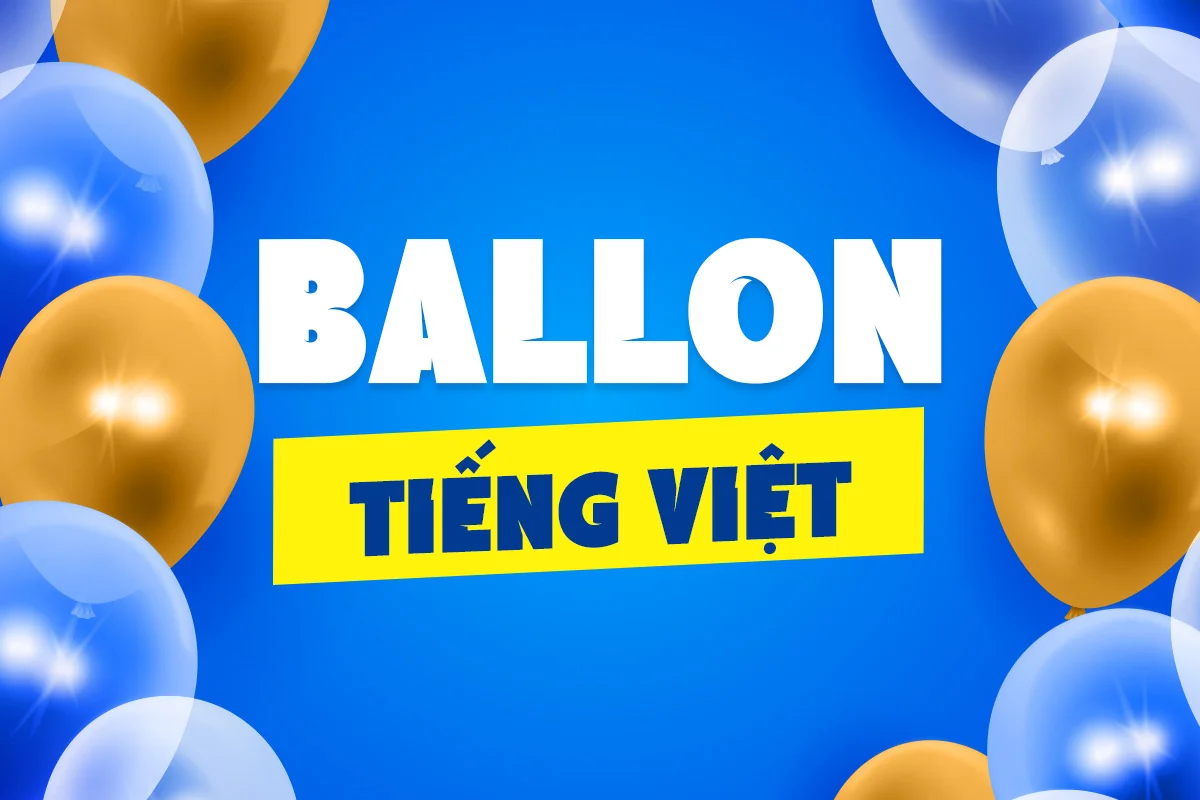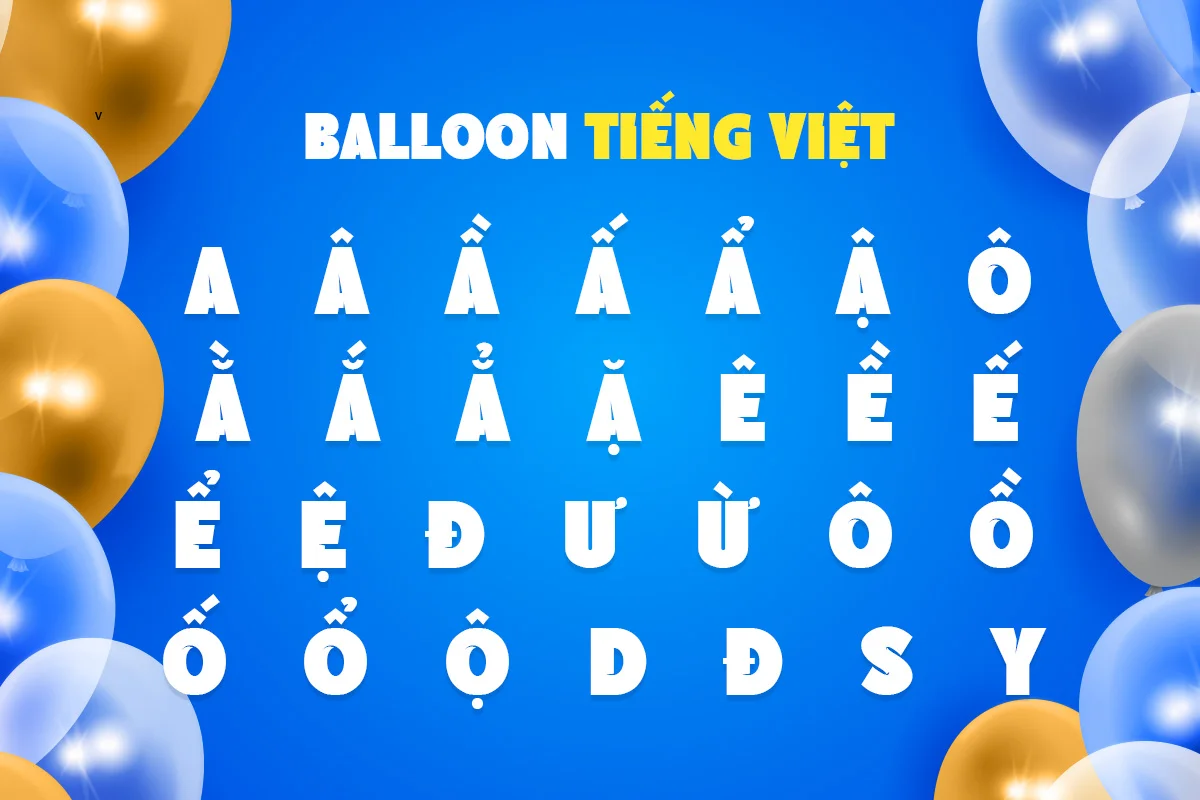
DVN Balloon mang phong cách khối chữ dày, góc cạnh nhưng được bo tròn vừa phải, tạo cảm giác hiện đại và chắc khỏe. Điểm đặc biệt nằm ở các đường cắt sắc nét trên thân chữ, như những lát chém đầy chủ ý, khiến font không chỉ mạnh mẽ mà còn có chiều sâu thị giác.
Sự kết hợp giữa nét phồng căng và vết cắt sắc gọn tạo nên cá tính khác biệt: vừa gợi không khí trẻ trung, vui tươi, vừa mang chất “bold” mạnh mẽ, dễ thu hút ánh nhìn. DVN Balloon phù hợp cho menu cà phê, trà sữa, poster trẻ em, bao bì sản phẩm, bảng hiệu hiện đại và cả những thiết kế cần sự năng động, táo bạo.